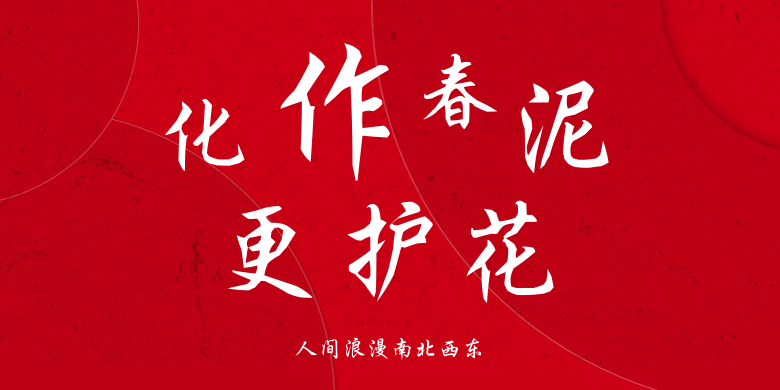
人间浪漫南北西东
人间浪漫南北西东,这款字体结构工整、笔画清晰,兼顾美观与易读性,适用于标题、正文、海报、包装、LOGO 等多种场景。字形优雅稳定,风格百搭耐看,适配日常排版与创意设计,让文字呈现更舒适、更具质感。人间浪漫南北西东一笔一画,皆是细节,以均衡的比例、流畅的线条打造舒适视觉体验,字形端正大气,风格简约现代。无论是商业设计、品牌宣传还是日常排版,都能轻松驾驭,让文字更有格调与力量。人间浪漫南北西东字体下载。